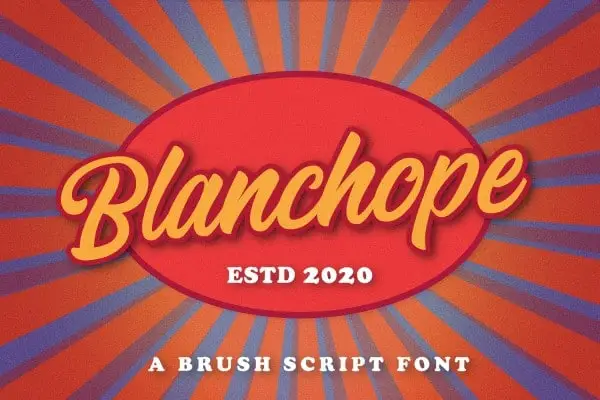
Blanchope Script Font – Download Grátis
A Blanchope Script Font é uma fonte script sofisticada e única, feita à mão por designers talentosos. Ela é perfeita para quem quer adicionar um toque especial a suas criações digitais. A Blanchope Script permite que você crie hand-lettering fluido, tornando-a ideal para o blogue, mídia social, marca, embalagem de produto, convites de casamento, headlines, sinalização, rótulos, assinaturas, capas de livros, posteres, frases e muito mais. Com a Blanchope Script em suas ferramentas digitais, você pode explorar novos estilos gráficos sem comprometer a qualidade da sua mensagem. Seja para uma marca que precisa de ser lembrada ou apenas um design que busca uma presença única, a Blanchope Script é o elemento perfeito para seu projeto.